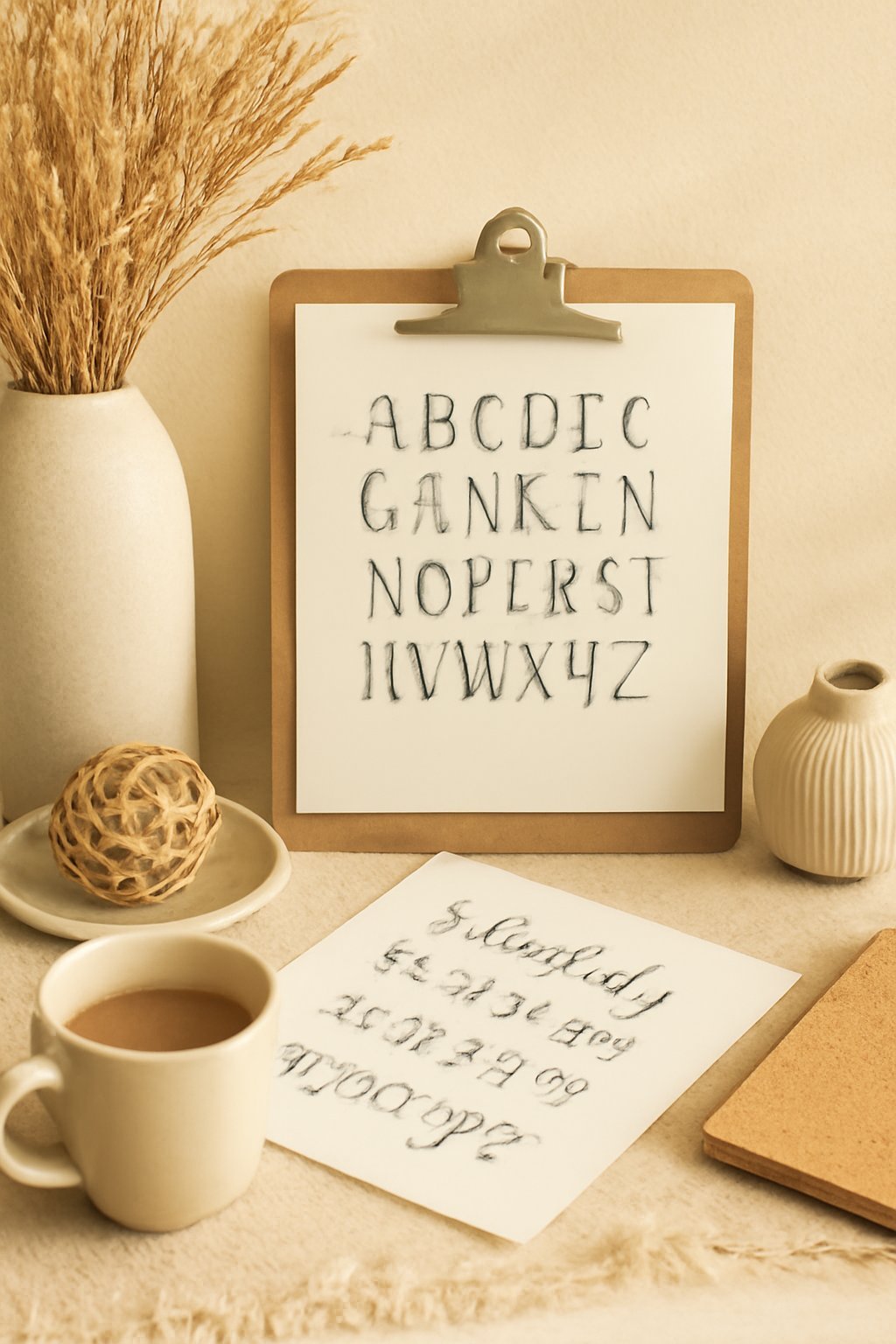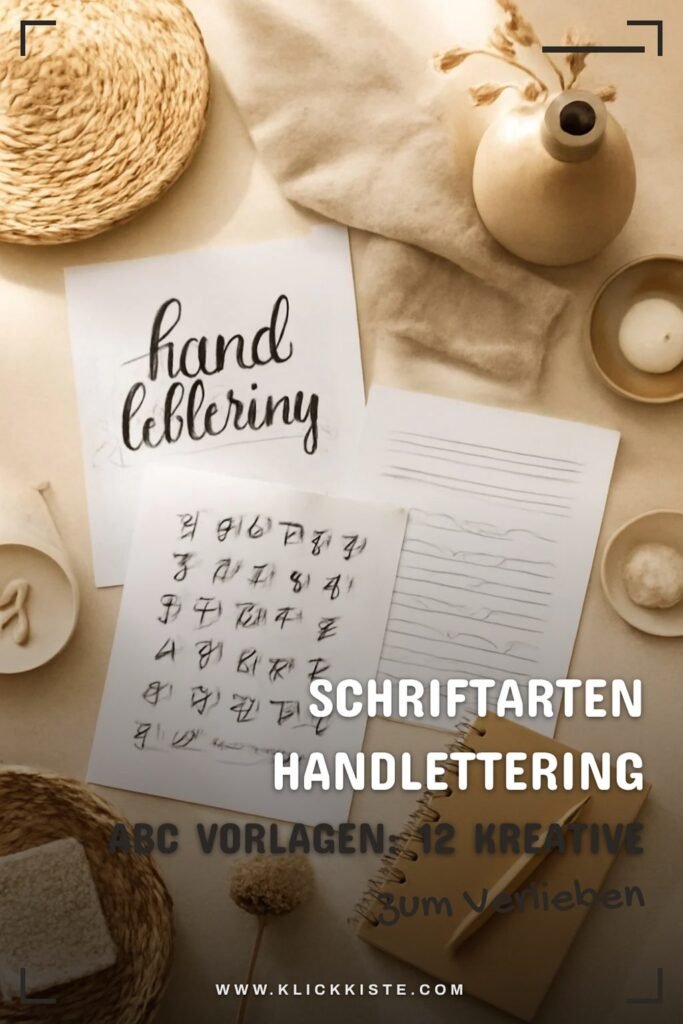
Schriftarten Handlettering Abc Vorlagen: Handlettering ist eine kreative Kunstform, die sich perfekt für DIY-Projekte eignet. Mit diesen Vorlagen kannst du…
Schriftarten Handlettering Abc Vorlagen: 12 kreative Ideen zum Selbermachen
Warum Schriftarten Handlettering Abc Vorlagen
Schriftarten Handlettering Abc Vorlagen sind ein wunderbarer Einstieg in die Welt des Handletterings, einer Kunstform, die ihren Ursprung in der Kalligrafie hat und heute bei Bastelfans äußerst beliebt ist. Diese Vorlagen bieten eine praktische Grundlage, um verschiedene Stile zu erkunden — von klassischen Schriftzügen bis hin zu modernen, verspielten Designs. Durch das Ausprobieren unterschiedlicher Schriftarten kannst du deinen eigenen Stil entwickeln und die Vielfalt dieser Kunstform kennenlernen. Bei der Auswahl von Schriftarten Handlettering Abc Vorlagen solltest du auf die Lesbarkeit und den individuellen Charme der Schriftzüge achten. Einige Designs sind geschwungen und filigran, während andere eher kräftig und klar sind. Es empfiehlt sich, mit Bleistift die Umrisse nachzuziehen, bevor die endgültige Farbe oder das Finish aufgetragen wird. So erhältst du mehr Sicherheit und kannst Fehler leichter korrigieren. Durch das Experimentieren mit verschiedenen Materialien, wie zum Beispiel Brush Pens oder Aquarellfarben, wird das Handlettering zu einem entspannten und kreativen Prozess, der dir hilft, deine persönliche Note zu entfalten.Schriftarten Handlettering Abc Vorlagen: 12 kreative Ideen zum Selbermachen
- Beginne damit, den Skizzenblock auf eine stabile Unterlage zu legen.
- Überlege dir nun, welchen Buchstaben du gestalten möchtest. Skizziere den Buchstaben mit dem Bleistift auf der Linie, die du zuvor gezogen hast.
- Sobald du mit der Skizze zufrieden bist, nimm den Fineliner zur Hand. Beginne, die Bleistiftlinien nachzuziehen und achte darauf, gleichmäßigen Druck auszuüben.
- Nachdem du den Buchstaben mit dem Fineliner nachgezogen hast, lasse die Tinte gut trocknen. Dies verhindert, dass die Tinte verwischt, wenn du die Bleistiftlinien radierst.
- Radier nun vorsichtig die Bleistiftlinien weg, sodass nur die schönen, klaren Buchstaben übrig bleiben. Achte darauf, dass du sanft arbeitest, um das Papier nicht zu beschädigen.
- Jetzt kannst du mit den Farben oder Markern beginnen, deine Buchstaben zu gestalten. Experimentiere mit verschiedenen Techniken wie Schattierungen oder Farbverläufen.
- Wenn du mehrere Buchstaben erstellt hast, kannst du sie zu einem Wort oder einem Spruch zusammenfügen.
- Um deine Vorlagen zu speichern, scanne sie ein und speichere sie digital. So kannst du sie immer wieder verwenden und anpassen.
Gelingtipps
- Nutze ein gutes Licht, um Details besser zu erkennen und präziser zu arbeiten.
- Übe die Buchstaben vorab auf einem separaten Blatt, um ein Gefühl für die Formen zu bekommen.
- Halte deine Materialien immer griffbereit, um den kreativen Fluss nicht zu unterbrechen.
- Beginne mit einfachen Buchstaben und arbeite dich zu komplexeren Formen vor, um Frustration zu vermeiden.
- Halte deine Hand ruhig, während du zeichnest, um gleichmäßige Linien zu erzielen.
Variationsideen
- Kalligrafie: Verwende spezielle Kalligrafie-Stifte für einen eleganteren Look.
- Aquarell: Experimentiere mit Aquarellfarben für sanfte Übergänge und Farbverläufe.
- Digitale Vorlagen: Nutze Grafiksoftware, um digitale Schriftarten zu erstellen.
Schritt 1
Beginne damit, den Skizzenblock auf eine stabile Unterlage zu legen. Nimm den Bleistift und zeichne leicht mit dem Lineal eine gerade Linie, um die Basis für deine Buchstaben zu schaffen. Diese Linie hilft dir, die Buchstaben gleichmäßig zu gestalten. Achte darauf, nicht zu fest zu drücken, damit die Bleistiftlinien später leicht radierbar sind.
Schritt 2
Überlege dir nun, welchen Buchstaben du gestalten möchtest. Skizziere den Buchstaben mit dem Bleistift auf der Linie, die du zuvor gezogen hast. Nutze einfache Formen, um die Proportionen festzulegen. Wenn du mit dem Ergebnis zufrieden bist, kannst du die Skizze vorsichtig verfeinern. Achte darauf, dass die Linien klar und deutlich sind.
Schritt 3
Sobald du mit der Skizze zufrieden bist, nimm den Fineliner zur Hand. Beginne, die Bleistiftlinien nachzuziehen und achte darauf, gleichmäßigen Druck auszuüben. Lass dir Zeit, um die Rundungen und Kanten gut zu gestalten. Der Fineliner sorgt dafür, dass die Buchstaben klar und präzise aussehen.
Schritt 4
Nachdem du den Buchstaben mit dem Fineliner nachgezogen hast, lasse die Tinte gut trocknen. Dies verhindert, dass die Tinte verwischt, wenn du die Bleistiftlinien radierst. Nutze die Wartezeit, um zu überlegen, welche Farben du für die Gestaltung verwenden möchtest.
Schritt 5
Radier nun vorsichtig die Bleistiftlinien weg, sodass nur die schönen, klaren Buchstaben übrig bleiben. Achte darauf, dass du sanft arbeitest, um das Papier nicht zu beschädigen. Der Unterschied zwischen den Bleistift- und Finelinerlinien wird nun deutlich sichtbar.
Schritt 6
Jetzt kannst du mit den Farben oder Markern beginnen, deine Buchstaben zu gestalten. Experimentiere mit verschiedenen Techniken wie Schattierungen oder Farbverläufen. Lass deiner Kreativität freien Lauf und mache jeden Buchstaben einzigartig.